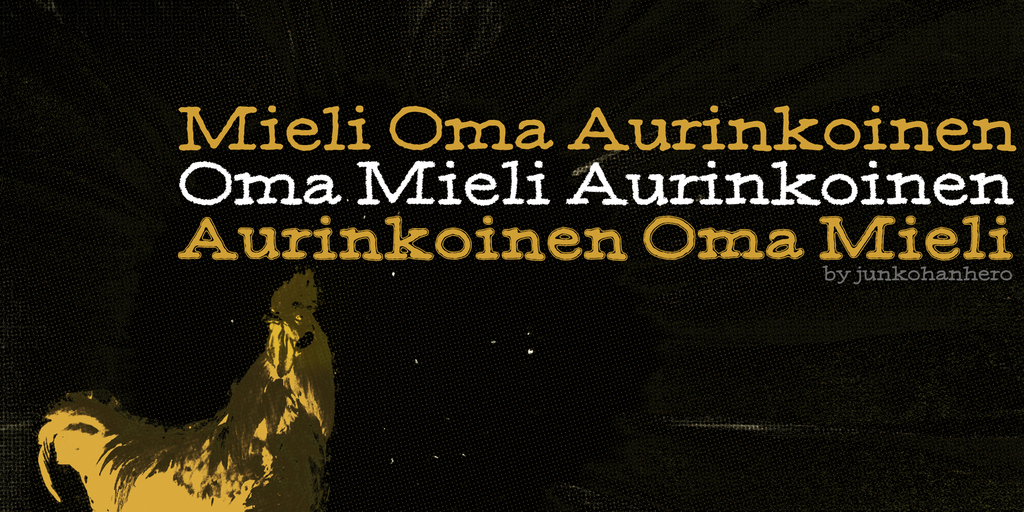
A MOA Font Family é uma família de fóntes leve e divertida desenvolvida pelo designer Hamilton. Ela é perfeita para projetos pessoais que exigem uma personalidade descontraída e um toque criativo, como cartões de aniversário ou listas de compras. O design da MOA combina ideias alegres com elegância sofisticada, tornando-a ideal para qualquer projeto visual que deseje um ar desconcertante e agradável aos olhos. Esta fonte é perfeita para quem busca uma alternativa leve ao uso tradicional de títulos e menções de texto. Com 14 fóntes diferentes, cada uma com seu próprio tom e estilo único, você pode escolher o que melhor se adequa à sua necessidade visual. Para usar a fonte em um projeto comercial, como logo ou logomarca, é necessário adquirir um licença de uso comercial por meio do PayPal, pagando 15€ (ou $20). Após realizar o pagamento, basta enviar um e-mail para Hamilton comprovando a compra. Você também pode usar o botão de doação localizado perto do botão de download, uma opção mais flexível. Através da MOA Font Family, você terá acesso a todas as fóntes no seu site ou em seu dispositivo, garantindo um ambiente de trabalho limpo e criativo. Não perca tempo, explore os vários recursos que a fonte oferece para criar designs únicos e lúdicos!